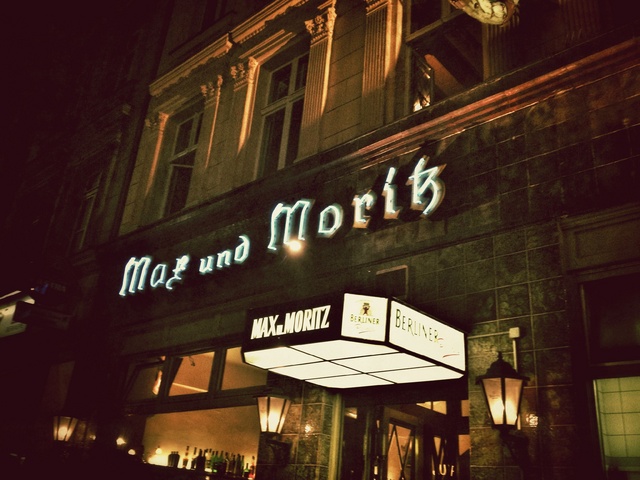
Neue Rechtschreibung?
Bleibt immer wieder die Frage, ob sich Schrift und deren Verständnis nicht am Leser orientieren soll … 99,9 % der Leser werden problemlos Brennpunkt lesen. Ein ewiger Wandel …
Ich hoffe doch sehr, Du habest unrecht.
Du hoffst, dass die Leute NICHT das Lesen, was beabsichtigt war? Seltsame Einstellung …
Der Vorführeffekt hat übrigens gleichmal zugeschlagen. Ich hab den Link angeklickt und sofort ohne das kleinste Stolpern Schänke gelesen. Erst beim tatsächlichen studieren der Einzelformen wurde mir bewusst, woran man da Anstoß nehmen könnte.
Du hoffst, dass die Leute NICHT das Lesen, was beabsichtigt war? Seltsame Einstellung …
Ich hoffe, daß Leute richtig und falsch unterscheiden können.
Übrigens … hatten wir nicht schon einmal festgestellt, daß es einen überseeischen Freefont-Klon der Klingspor gibt, wo das tz auf der k-Taste liegt? Ich meine mich zu erinnern …
Tja, da wäre dann wieder die Frage wer uns definiert, was richtig und falsch ist …
»Historisch richtig« ist mit Sicherheit kein Argument, da deine eigenen Texte mit Sicherheit auch vollen »historisch falsch« benutzter Begriffe sind.
Die Schrift mit dieser Belegung heißt übrigens Killigrew.
Tja, da wäre dann wieder die Frage wer uns definiert, was richtig und falsch ist …
Daß ein tz kein k ist, sollte ja eigentlich unstrittig sein und durch die bloße optische Ähnlichkeit nicht in Frage stehen. Sonst könnte man ja gleich ein B statt des Versal-ß als eine akzeptable Option erklären ;-) . Manchmal erstaunt es mich doch noch, wie weit Du in Deinem Ultra-Pragmatismus gehst.
Die Schrift mit dieser Belegung heißt übrigens Killigrew.
… und man sollte sie steinigen. :mad:
Ich will das Beispiel ja gar nicht verteidigen, sondern stelle nur wie immer die Argumentation in Frage.
Wird können uns darauf einigen, dass die Schrift »falsch digitalisiert« wurde (tz-Ligatur auf Position des k abgelegt) und es ist völlig erwartungsgemäß, dass so ein Beispiel in Typo-Kreisen als Fundstück die Runde macht.
Aber man kann es eben auch aus Nutzersicht betrachten: Da wählt jemand eine Schrift und setzt einen Text und beim Leser des Textes wird der ohne Probleme genau so verstanden, wie vom Absender beabsichtigt. Wo ist jetzt also das Problem? Da macht doch »richtiger« Fraktursatz mit ſ das als f gelesen wird, x das als r gelesen wird usw. viel mehr Probleme als dieses vermeintliche Paradebeispiel eines ahnungslosen Schriftdigitalisierers.
Oder um es mit einem Beispiel aus der Wortwahl zu zeigen:
Da benutzt einer das Wort Versalien und der Hörer kennt das Wort und versteht es genau so wie der Sprecher es gemeint hat. Ein Dritter weiß nun aber, dass Versalie ursprünglich ausschließlich Initialen bezeichnete und von Sprecher und Hörer also in diesem Sinne historisch falsch verwendet wurde. Dasselbe in Grün.
Daher störe ich mich dann an der Aussage, dass jemand sagt »hoffentlich versteht der Leser das falsch«, nur weil man selbst weiß, dass es »historisch falsch« ist. Dass Texte so gelesen/verstanden werden wie sie gemeint sind, ist nun eine nicht so abwegige Hoffnung.
Du denkst hier viel zu taktisch / anlaßbezogen und viel zu wenig strategisch / global. Solche Sachen wie die k-tz-Substitution fördern die allgemeine Verblödung und Illiteralisierung und sind somit mittelfristig der Fertigkeit verstehenden Lesens abträglich. Daran ändert auch nichts, daß es erst einmal zu funktionieren scheint. Aber hier wird wohl mein Dogmatismus mit Deinem Pragmatismus mal wieder nicht übereinkommen. :gimmifive:
Solche Sachen wie die k-tz-Substitution fördern die allgemeine Verblödung und Illiteralisierung …
Inwiefern?
Du denkst hier viel zu taktisch / anlaßbezogen und viel zu wenig strategisch / global.
Stimmt! Man sollte sich nicht mit solchen Einzel-Logo-Beispielen aufhalten, sondern lieber gegen dauerhafte und konsequente Falschschreibungen wie Citat vorgehen – die richten mehr Schaden an als eine einzelne Stadionschänke …
Wann stand das eigentlich zuletzt in Einklang mit der amtlichen deutschen Rechtschreibung? ;-)
Laut einer Änderungsliste der Reform von 1901 war zuvor nur Citat richtig, danach sowohl Zitat als auch Citat. Im Duden von 1926 ist Citat nicht mehr enthalten (da anscheinend schnell ausgestorben).
Dafür gibt es Citrat, sieht ähnlich aus und macht auch manche sauer ;-)
Solche Sachen wie die k-tz-Substitution fördern die allgemeine Verblödung und Illiteralisierung und sind somit mittelfristig der Fertigkeit verstehenden Lesens abträglich.
Das ist doch Murks! Wie soll denn eine Glyphe, die historisch falsch aber faktisch richtig interpretiert wird, die Illiteralisierung fördern? Oder gar dem verstehenden Lesen abträglich sein? Gebrochene Schriften sind außerhalb aus unserer Wahrnehmung (Wann wurde das letzte Buch in Fraktur gedruckt (jenseits von Nischenwerken) oder gar eine Zeitung (dito)?) und deswegen sollten wir alle froh sein, dass es Menschen gibt, die die Formensprache der Gebrochenen in unsere Umwelt zu reintegrieren versuchen. Deine Argumentation macht nur Sinn, wenn diejenigen, die die Zielgruppe des Schildes bilden, Druckwerke vor 1940 lesen würden. Die Druckwerke, die die Allgemeinheit interessen, sind inzwischen in Antiqua oder Grotesk gesetzt, und diejenigen, die in Gebrochenen gesetzte Druckwerke genießen wollen, beherrschen die entsprechende Formensprache. Die einzigen, die sich darüber in Breite aufregen, sind, um mal einen Anglizismus zu nutzen, grammarnazis (gibt es schon die typonazis?).
Wenn Du Ralf lieb bittest, benennt er ja vielleicht meinen Account um. ;-)
Ach komm, so schreibts doch mal ein Buch zusammen, der Ralf und du: Dogma und Pragma – Far Eastern Artistic Rechtschreibers (FEAR). Und damit ihr euch zur Abwechslung auch einmal gemeinsam an etwas enervieren tätet, gäb's das Werk ausschließlich in Kleinschrieb und fürstentum·liechtensteinisch-schweizerischer "ß"-Regelung.
Würdest Du so ein Buch kaufen wollen?
… fürstentum·liechtensteinisch-schweizerischer "ß"-Regelung.
Hier von »Regelung« zu sprechen, ist ja auch etwas euphemistisch. »Endlösung« wäre da wohl passender.
Würdest Du so ein Buch kaufen wollen?
Unbedingt.
… »Endlösung« …
… ist demnach kakophemistisch.